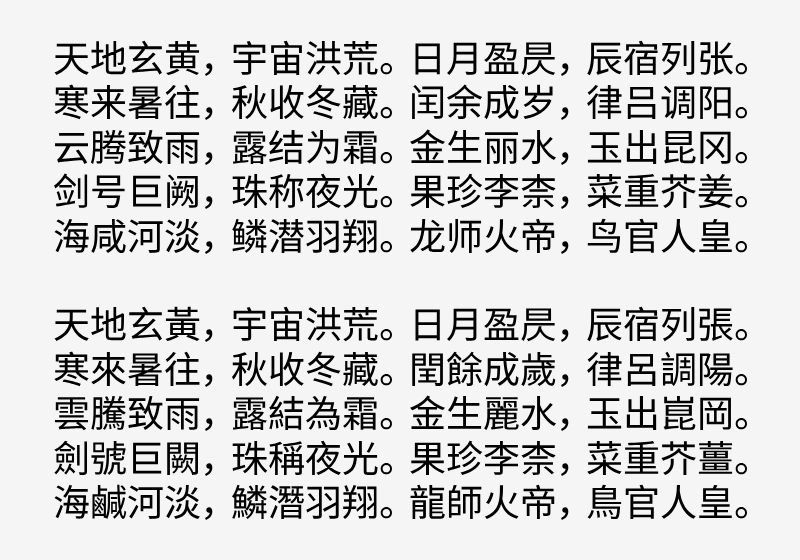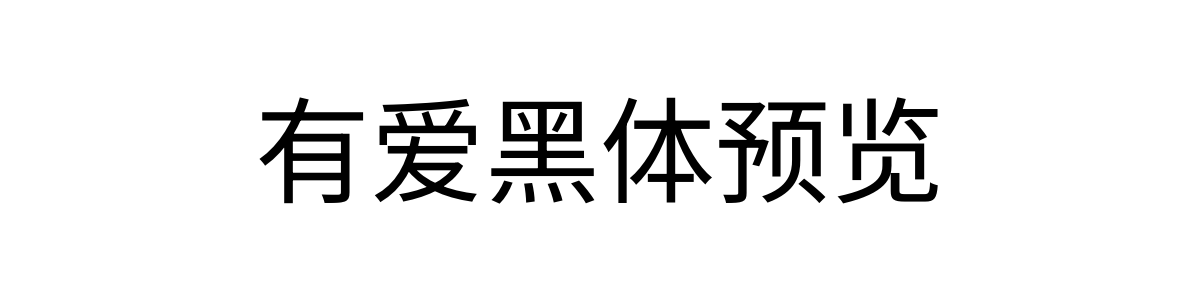
有爱黑体 2026年3月29日 下午4:37 • 多语言字体 • 阅读 483 目录 字体预览字体风格字体下载 有爱黑体(Nowar Sans)是面向《魔兽世界》与怀旧服制作的开源内嵌字体,由 Noto Sans 与思源黑体整合而成。 这款字体针对游戏界面做了专门适配,不管是任务描述还是物品说明,都能完整、准确地显示,同时也考虑到了玩家长时间游戏容易产生视觉疲劳的问题,在阅读体验上做了优化。 字体预览 有爱黑体 选择预设预览文本 选择预设文字 天地玄黄,宇宙洪荒。 雲騰致雨,露結為霜。 Hello, World 1234567890 !,、。!?:;“”‘’ A- A+ 自定义预览文本 选择字体字重 Light Regular Bold 字体风格 有爱黑体主打实用与易读,字形结构稳当清晰,笔画简洁、粗细适中,在游戏里各种复杂场景下都能清晰识别,也能缓解长时间看文字带来的眼部负担。 字体下载 有爱黑体 下载次数 50 字体类型 黑体 授权协议 OFL 授权类型 免费商用 刷新 OFL日文简体繁体韩文黑体阅读字体 赞 (0) 0 0 生成海报 相关推荐 多语言字体 思源黑体 思源黑体(Source Han Sans / Noto Sans CJK)是 Adobe 与 Google 耗时三年联合打造的开源黑体,于 2014 年 7 月正式发布,也是业内首个真正覆盖全 CJK 区域的通用字体。这款字体支持简繁中文、日文、韩文,搭配完整的拉丁字符集,单字体字符量超 65000 个,全家族字形总数接近 50 万,是目前字库最完整、应用最广泛的免费商用字体之一。 2026年3月27日 7.1K5 多语言字体 快去写作业CJK 快去写作业CJK(CEF Fonts CJK)是一款完全由鼠标绘制、覆盖海量字符,专为艺术创作设计的“仿”手写风格泛CJK字体。该字体由个人开发者从2020年4月25日起,历时两年多,纯粹使用鼠标(而非数位板)逐个点画完成。 2026年1月16日 2990 多语言字体 更纱黑体 更纱黑体(Sarasa Gothic)是一款面向中日韩与英文混排场景深度优化的开源免费字体,以 100% 缩放下极佳的屏幕显示效果和可读性为亮点。它由西文优质字体 Inter、编程等宽字体 Iosevka ,搭配思源黑体的 CJK 部分整合而成。 2026年4月3日 1.3K1 多语言字体 寒蝉圆黑体 寒蝉圆黑体(Chill Round Gothic)是一款通过算法对思源黑体进行精准圆角化转换,兼顾结构严谨与视觉亲和力的开源圆体。采用特定算法按比例对原字体的所有笔画转折处进行“原汁原味”的圆角化处理,未改变原有字形结构和笔画走势,从而在最大程度上保留了思源黑体均衡、可靠的骨架。 2026年1月23日 6050 多语言字体 有爱锐方 有爱锐方(Nowar C²)是专门给《魔兽世界》和怀旧服做的一款游戏字体,能完整显示游戏里所有语言内容。它对字形做了专门优化,不管在什么分辨率下,文字显示都很清晰锐利,游戏界面里的字看着更清楚。有爱锐方的重点就是边缘干净利落,通过专门调整,解决了屏幕上文字模糊、有毛边的问题。就算在战斗这种画面复杂、节奏快的场景里,字也很清楚,看信息一眼就能认出来。 2026年3月28日 6000 发表回复 请登录后评论...登录后才能评论 提交